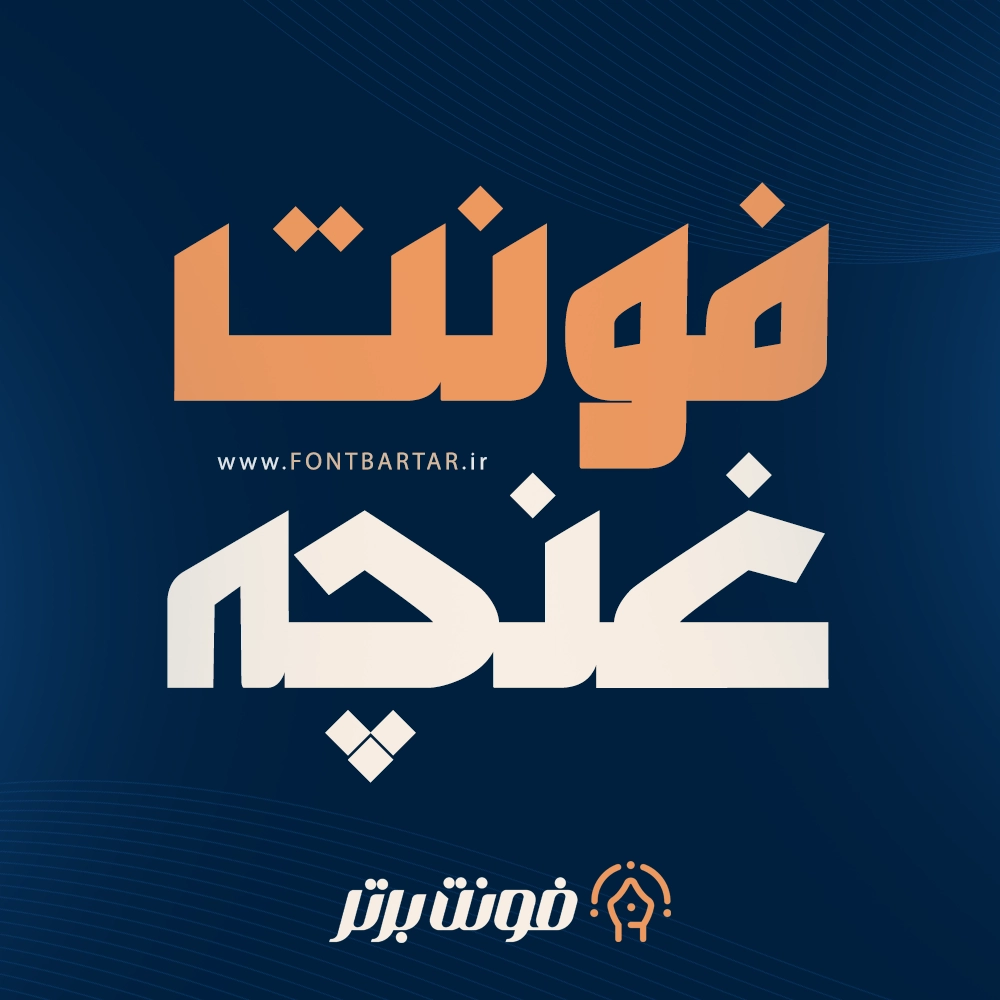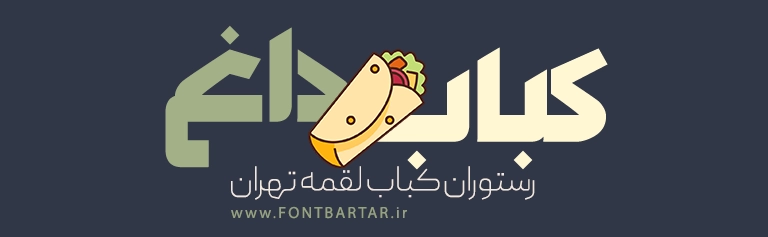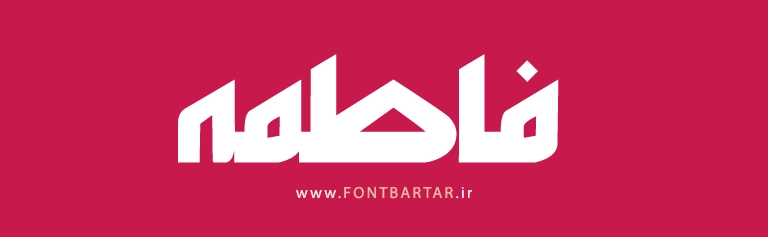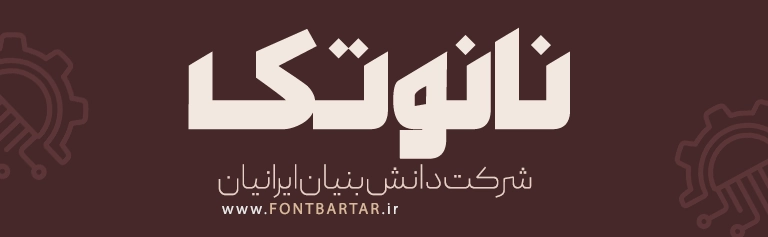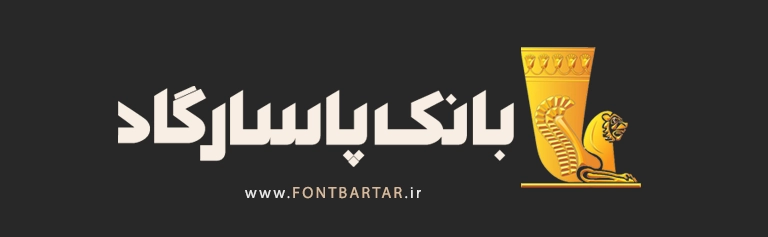
فونت فارسی غنچه یکی از فونت های فارسی خاص و متفاوت است که با طراحی مدرن و ساختار گرافیکی منحصربهفرد، انتخابی عالی برای طراحان حرفهای محسوب میشود. اگر به دنبال فونت فارسی آنلاین هستید که در نگاه اول توجه مخاطب را جلب کند و برای طراحی لوگو، پوستر، بنر تبلیغاتی و محتوای دیجیتال کاربردی باشد، فونت غنچه میتواند پاسخ نیاز شما باشد. فونت فارسی باحال با فرم هندسی و ضخامت متعادل حروف، خوانایی مناسب را در کنار جلوه بصری قوی ارائه میدهد و برای پروژههای رسمی و خلاقانه بهصورت همزمان قابل استفاده است.
ویژگیهای فونت فارسی غنچه
- طراحی خاص و مدرن با فرمهای گرافیکی جذاب
- مناسب طراحی لوگو، تیتر، پوستر و بنر تبلیغاتی
- خوانایی بالا در سایزهای بزرگ و متوسط
- هماهنگ با سلیقه طراحی مدرن و مینیمال
- قابل استفاده در پروژههای چاپی و دیجیتال
کاربردهای فونت فارسی جدید غنچه در طراحی
فونت غنچه به دلیل ساختار خاص خود، در حوزههای مختلف طراحی کاربرد دارد. برخی از مهمترین موارد استفاده عبارتاند از:
- طراحی لوگو و برندینگ
- طراحی پوسترهای تبلیغاتی و فرهنگی
- ساخت بنرهای اینستاگرامی و استوری
- طراحی کاور پست و محتوای شبکههای اجتماعی
- استفاده در تیتر وبسایتها و صفحات فرود
چرا فونت غنچه برای طراحان حرفهای مناسب است؟
در دنیای طراحی، انتخاب فونت تأثیر مستقیمی بر درک مخاطب از برند دارد. فونت غنچه با طراحی متفاوت خود به شما کمک میکند:
- هویت بصری منحصربهفرد بسازید
- پیام برند را سریعتر منتقل کنید
- نرخ تعامل کاربران را افزایش دهید
- پروژههای طراحی را حرفهایتر ارائه دهید
فونت فارسی زیبا غنچه برای طراحانی که به جزئیات، کیفیت و تمایز اهمیت میدهند، گزینهای بسیار مناسب است.
فونت غنچه برای چه نوع طراحیهایی مناسب است؟
فونت غنچه بیشتر برای طراحی لوگو، پوستر، بنر تبلیغاتی و تیترهای گرافیکی استفاده میشود و برای متون طولانی توصیه نمیشود.
آیا فونت غنچه خوانایی خوبی دارد؟
بله، این فونت در سایزهای متوسط و بزرگ خوانایی بسیار خوبی دارد و برای تیتر و المانهای اصلی طراحی مناسب است.